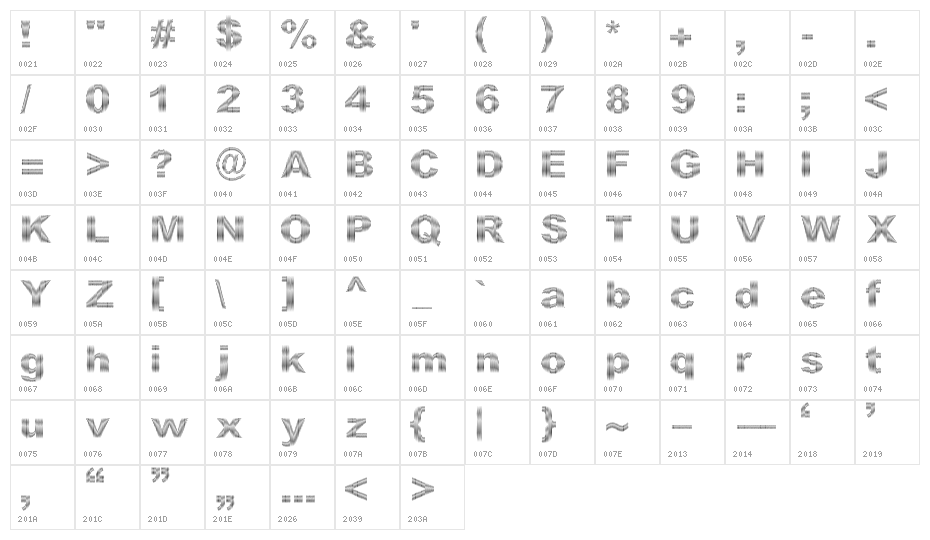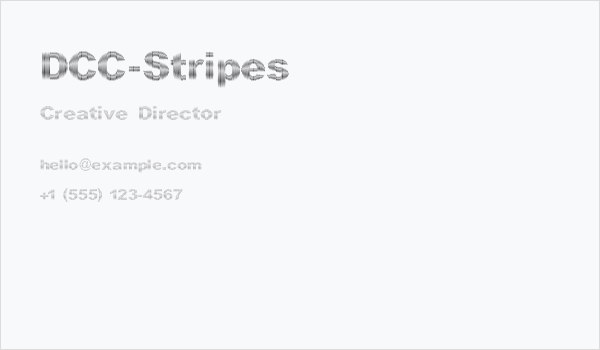
DCC-Stripes Font
| Общий стиль | Modern, Decorative |
| Рекомендуемые проекты | Ideal for branding, posters, headlines, and any project requiring a bold, eye-catching typeface. |